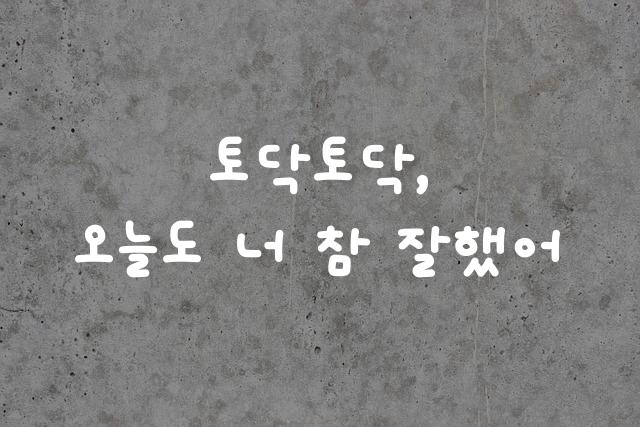
제주돌담체는 얼리폰트에서 제작한 귀여우면서도 독특한 감성을 담은 두꺼운 장식 손글씨 폰트입니다. 이 폰트는 편안하고 친근한 느낌을 주어 사용자에게 따뜻함을 전달합니다.
제주돌담체은(는)
단단함, 별모양/패턴, 손글씨, 감성적인, 장식 스타일, 굵은 고딕, 두꺼운 스타일, 귀여운 스타일 계열의 생김새를 가지고 있으며
초대장, 카페 메뉴, 인사말 카드 등에서 자주 활용되며, 효과적인 메시지 전달에 적합합니다.
이 폰트는 음식/식음료, 라이프스타일, 관광/여행 분야에 잘 어울리며,
자연스러운, 편안한, 친근한 느낌을 담고 있는 것이 특징입니다.